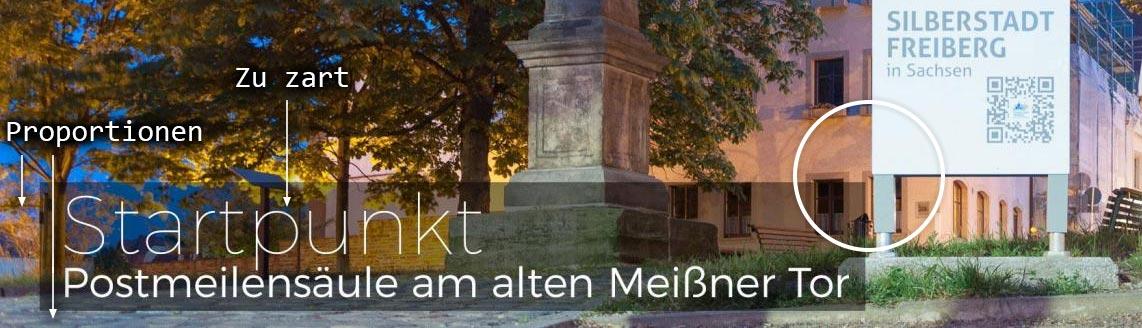
Schrift Midsummer Half
Sicher gibt es bessere Lösungen aber für meine Zwecke ...
Wieso? Das war doch eine gute Lösung mit der Korrektur in Photoshop. Nur Spiegelungen bekommst damit halt nicht so leicht weg. So ein Polfilter ist aber eine sehr sinnvolle Investition. Den braucht man auch nicht nur bei spiegelnden Flächen. Im Falle des Fotos von dem Plakat hätte er dir aber nicht viel genützt, weil du im 90°-Winkel zur Scheibe fotografiert hast. Außerdem ist die Spiegelung extrem. Da hättest du auf eine andere Lichtsituation warten müssen. Die anderen Fotos finde ich aber gelungen. Geh in den nächsten Nächten doch nochmal los und leg dir einen Vorrat für weitere Banner an. Vielleicht mit ein paar Läufern. Für den übernächsten Mitsommerlauf.
Das war doch eine gute Lösung mit der Korrektur in Photoshop
Mit Lightroom ...  (Funktion Objektivkorrekturen und Transformieren (Upright)
Geh in den nächsten Nächten doch nochmal los und leg dir einen Vorrat für weitere Banner an.
Mache ich :-) War die erste Aktion in dieser Richtung überhaupt und sollte eigentlich nur ein Test sein. Bin jetzt schon zufrieden mit den meisten Fotos und jetzt halt noch ein paar mehr Motive und dann ist gut ...
Passt die Beschriftung jetzt so?
Noch ein Tipp für deine Fototour:
Nimm die Fotos von derselben Position (Stativ) und in derselben Beleuchtungssituation mit und ohne Läufer auf. Dann kannst du sie hinterher in Ebenen übereinanderlegen und Läufer recht leicht anders gruppieren oder entfernen.
Die Schrift ist jetzt in Regular und Light deutlicher zu lesen und dazu die Farbe von Mittsommer (Banner). Bin trotzdem nicht sicher ob das so gut zu lesen ist. Ansonsten bleibt dann wohl nur ein Dunkler Balken unten und da die Schrift rein.
Na du bist ja lustig. Jetzt ist die zweite Zeile zu zart. :-)
Jetzt nicht mehr. Du Schlingel hast schon wieder das Bild ausgetauscht. Aber an der Farbe hätte ich nichts geändert.
Bzw. zu π-gelb, wenn du verstehst :shock:
Ansonsten fehlt mir der Zusammenhang der Typo und Bildsprache mit der von deinem Plakat :-?
Bzw. zu π-gelb, wenn du verstehst
Verstehe ich leider nicht ...    und bei Punkt 2 (Typo und Bildsprache) müsstest Du mir auch auf die Sprünge helfen :-)
müsste eigentlich auch ππ-gelb heißen ;-) …
müsste eigentlich auch ππ-gelb heißen
Noch nie gehört ... Ist halt in dem Fall das Gelb vom Banner und deshalb war das die Idee dahinter
Noch nie gehört
Du kennst den griechischen Buchstaben Pi? Und wenn man zwei Pis direkt in einem Wort hintereinander schreibt, ergibt das ein kleines Geschäft.
:-):-) Wieder was gelernt
Aber bevor Du das Falsche lernst: Mit dem ππ-gelb hat Bertel die Farbe gemeint, die man normalerweise Plissee-Gelb nennt (aber ohne das erste »l« und »e«).
So?
Fotorealismus und eine symbolhafte Explosion am Himmel. Irgendwie passt das nicht zusammen. Vielleicht kannst du stattdessen einen Supernovarest einarbeiten. Okay, unter dem Beschuss harter Strahlung schafft der Läufer keine fünf Kilometer. Aber vielleicht kannst du die Farben von Himmel und Explosion angleichen. Die beißen sich nämlich schlimmer als freilaufende Luden-Hunde Läufer.
vor 4 Minuten schrieb Arno Enslin:
Aber vielleicht kannst du die Farben von Himmel und Explosion angleichen.
Wird zu aufwendig und so soll es ja auch nicht sein. Dann lasse ich es lieber ganz und bleibe beim Foto mit den 2 Textzeilen. Ansonsten wird es bei jedem weiteren Foto dann ja auch wieder kompliziert und da stehen Aufwand und Nutzen in keinem Verhältnis.
vor 4 Minuten schrieb Heike & Stefan:
Wird zu aufwendig
Eigentlich nicht. Du könntest die Farben der Explosion, die sich mit dem Hintergrund beißen, neutralisieren und halb transparent machen.
Es böte sich auch an, statt der symbolhaften Explosion einen am Boden verankerten Ballon einzumontieren.
Übrigens passt das Rechteck, mit dem die beiden Zeilen hinterlegt sind, gar nicht. Und du hast Zollzeichen verwendet anstelle von Anführungszeichen. Und das Größenverhältnis der beiden Zeilen ist zu extrem. Die Position des Rechtecks wirkt auch etwas willkürlich.
vor 8 Minuten schrieb Arno Enslin:
Es böte sich auch an, statt der symbolhaften Explosion einen am Boden verankerten Ballon einzumontieren.
Gute Idee - das Wäre noch einen Versuch wert :-)
vor 9 Minuten schrieb Arno Enslin:
Ohne das Rechteck funktioniert ist, die Bilder sind ja alle dann noch später aufgenommen und da ist es entsprechend dunkel. Also das Gelb wieder weg und das Rechteck auch und dafür die Schrift etwas größer.
Ballon oder etwas in der Richtung funktioniert nicht und sieht blöd aus. Bei dem Foto hier mag das noch gehen, bei den anderen in der Stadt funktiniert es überhaupt nicht und auch die Explosion sieht albern aus.
Als 2. Variante die Schrift in Gelb wie gehabt aber ohne Rechteck - gefällt mir auch